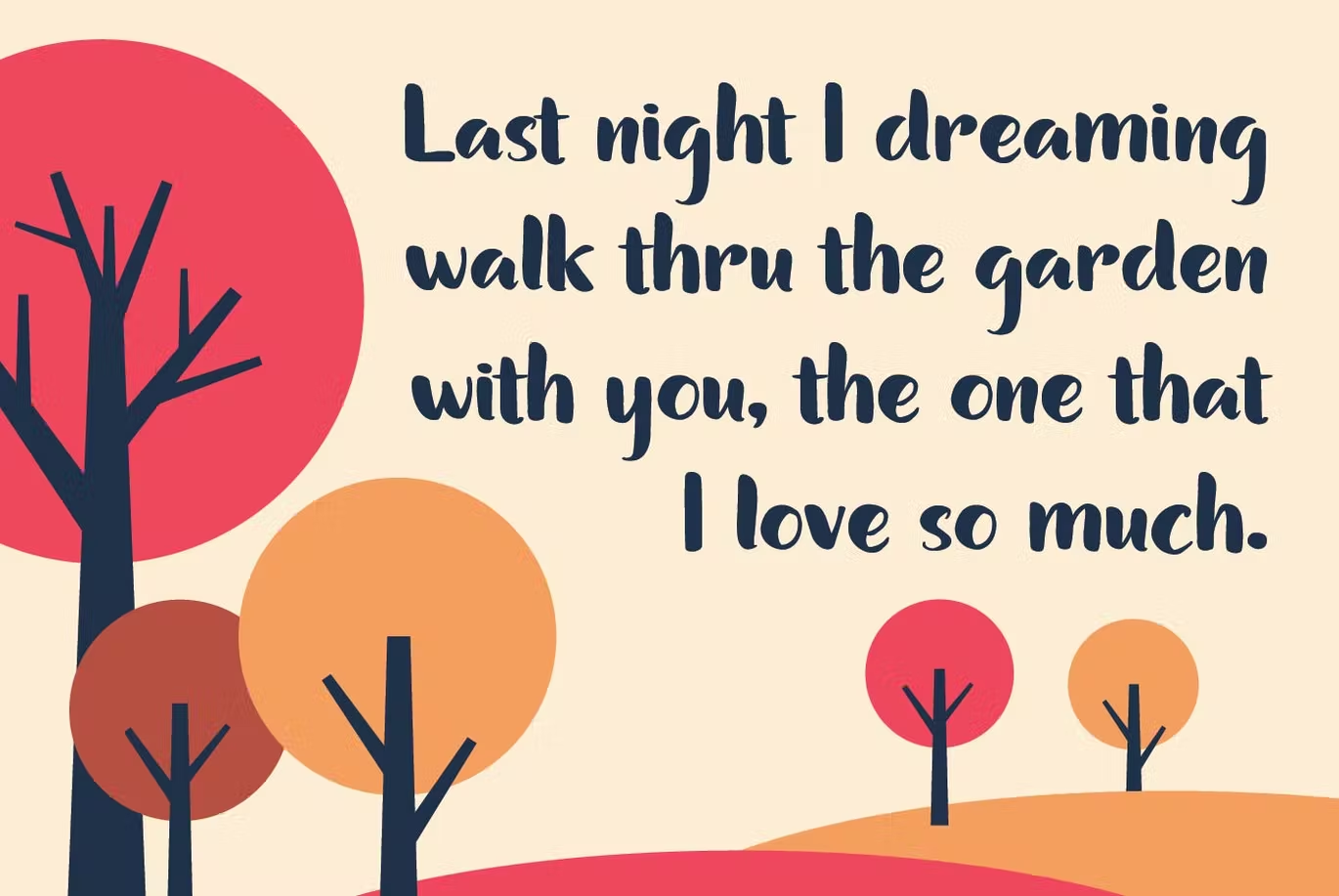
Bundhers Font
Description de Bundhers Font
Présentation de Bhunders – une police manuscrite amusante. Avec cette police, vous pouvez l’utiliser pour la couverture de livres et de magazines, les réseaux sociaux, les titres, les logos, l’artisanat, les marchandises, les produits numériques, etc.
Cette police est disponible en majuscules, minuscules, chiffres, symboles et également en accent multilingue.
Vue des polices Bbundhers